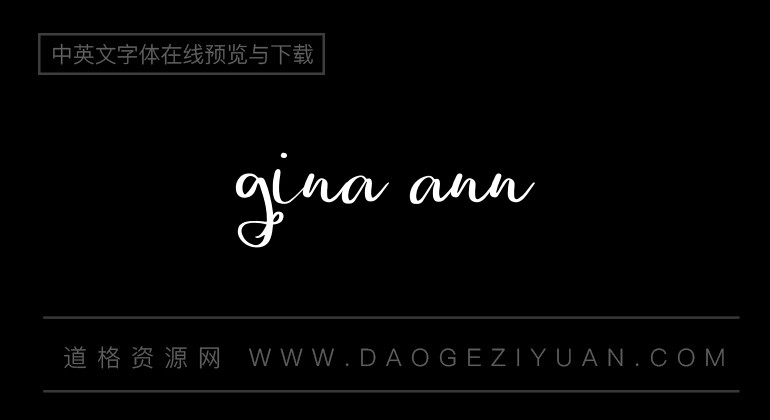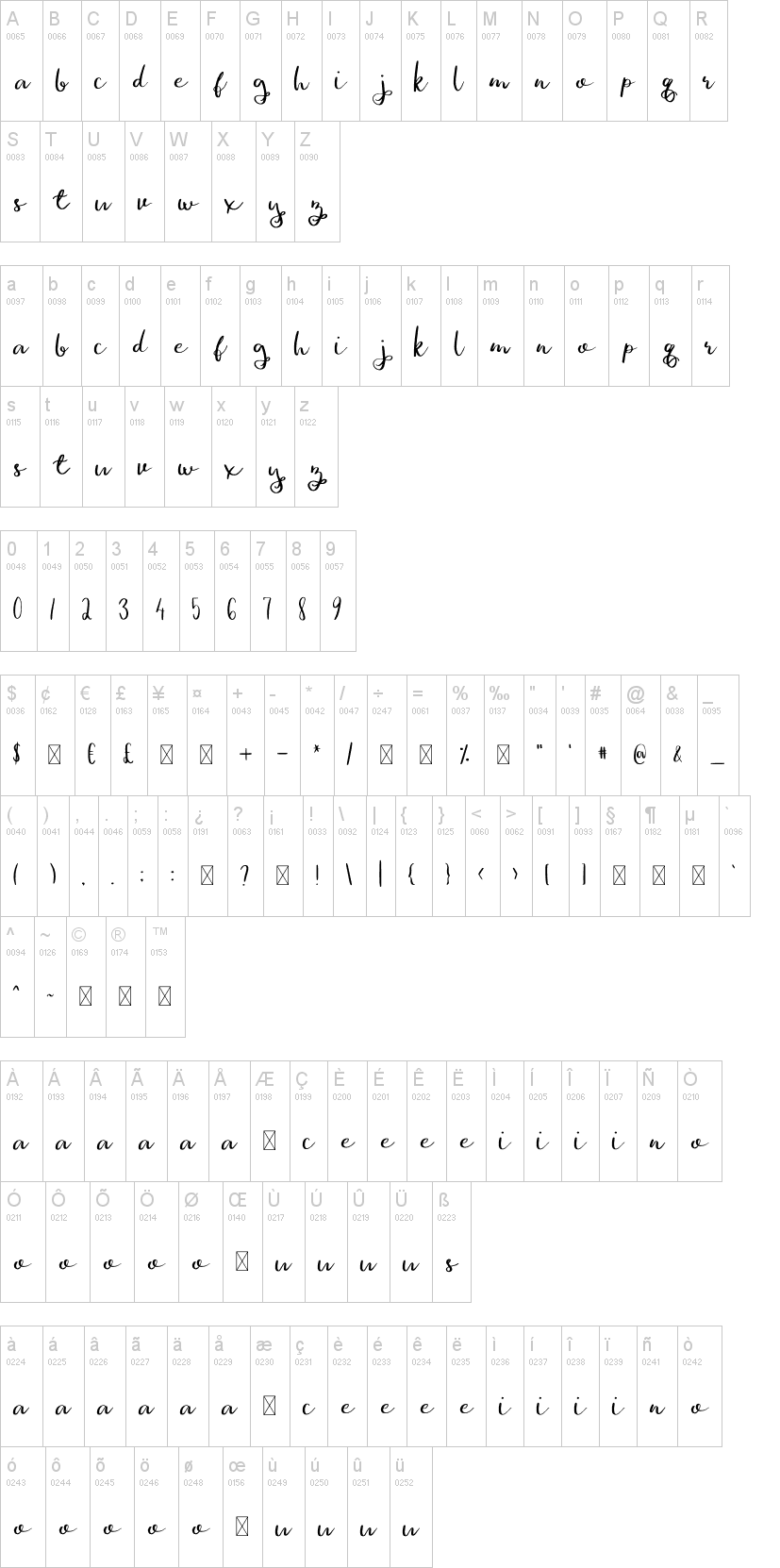
Gina Ann 字体是一款现代风格的手写字体,由设计师Gina Ann创作。它采用细腻的线条,给人一种温和、柔和、温暖的感觉。它适用于各种场景,既可以用于商业设计,也可以用于日常生活中的文字排版,还可以用于时尚类的LOGO设计。Gina Ann字体具有清晰的轮廓和舒适的曲线,可以为用户提供最佳的视觉体验。内容介绍
Gina Ann是一款非常不错的手写艺术字体,具有很好的视觉感,适合于文化类的宣传设计、商业类品牌的广告和产品包装设计以及个性化文字排版等较多场景。